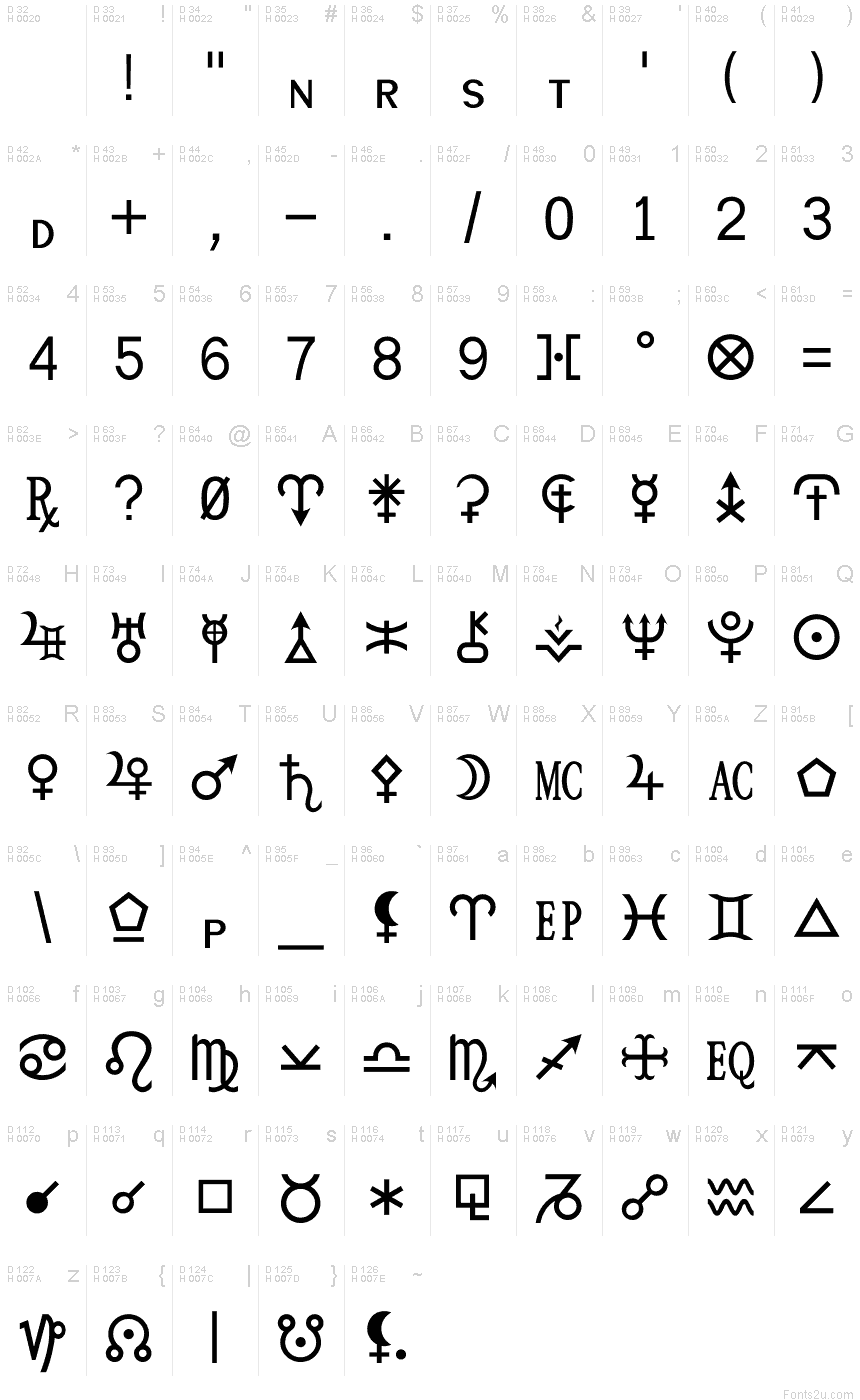
HamburgSymbols
Hamburg Symbols to darmowy, esoteryczny krój pisma typu dingbat. Jego znaki łączą astrologiczne krzywe, alchemiczne symbole i kwadratowe, geometryczne ramki w gęste, nasycone tuszem glify, które sprawiają wrażenie zarówno archaicznych, jak i precyzyjnie zaprojektowanych. Kreski są ciężkie i zdecydowane, dzięki czemu każdy znak odbija się na stronie niczym pieczęć, natychmiastowo nadając projektom rytualny, zakodowany klimat bez potrzeby tworzenia skomplikowanych ilustracji.
Dzięki Hamburg Symbols możesz dodać tajemnicze ikony do projektów kart tarota, plakatów o tematyce okultystycznej, podręczników do gier RPG, okładek albumów, map fantasy czy ozdobników rozdziałów w książkach. Ten darmowy font świetnie sprawdza się w większych rozmiarach jako główny element wizualny, wsparty przejrzystym krojem bezszeryfowym lub szeryfowym w tekście głównym, co pozwala zachować mistyczną czytelność.
Symbols for Uranian Astrology, asteroids, and personal points.